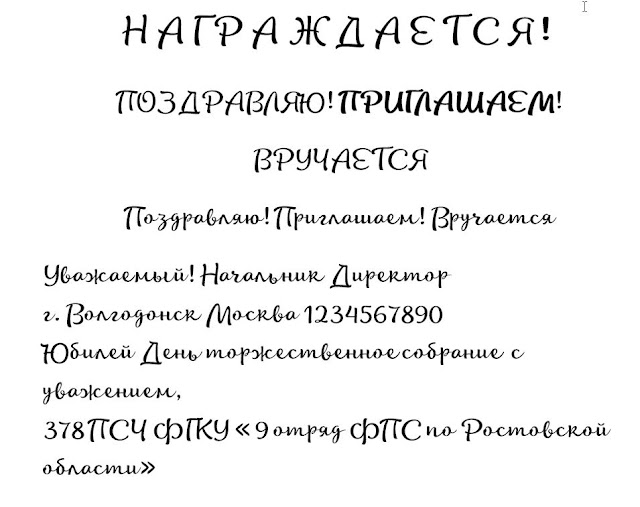
Правила выбора шрифтов. Внедрение шрифта в презентацию. презентация, доклад
Шрифты:
как выбрать шрифт?
как внедрить шрифт в презентацию?
MS Office Power Point
Как выбрать шрифт для презентации
Правило первое
ШРИФТ ДОЛЖЕН БЫТЬ ЛЕГКО ЧИТАЕМЫМ.
Потому отдавайте предпочтение шрифтам без засечек. Образцами таких шрифтов являются Arial, Calibri, Century Gothic, Verdana.
Это не значит, что нужно совсем отказаться от изысканных шрифтов с засечками. Используйте их в заголовках – крупные буквы будут читаться легче.
Как выбрать шрифт для презентации
Правило второе
ИСПОЛЬЗУЙТЕ ДОСТАТОЧНЫЙ РАЗМЕР ШРИФТА.
Помните, что шрифт с кеглем менее 18 вообще неприемлем для публичных выступлений.
Шрифт размером до 24 подходит для идеальных условий – когда проектор яркий, освещение соответствующее, и аудитория сидит недалеко. Так что лучше всего использовать размер шрифта не менее 24.
Как выбрать шрифт для презентации
Правило третье
НЕ ПЕРЕБОРЩИТЕ С КОЛИЧЕСТВОМ.
Слайды, на которых слишком большой разброс в размерах шрифтов или слайды, где использовано слишком много разных шрифтов, выглядят нагромождёнными и тяжелы для восприятия.
Удобно использовать один шрифт для заголовков и один для основного текста.
Как выбрать шрифт для презентации
Правило четвёртое
РАССТАВЛЯЙТЕ АКЦЕНТЫ ПРАВИЛЬНО.
Как выбрать шрифт для презентации
Правило пятое
ПОМНИТЕ О СОЧЕТАЕМОСТИ
Шрифты, которые Вы используете, должны соответствовать общему дизайну презентации и не конфликтовать между собой.
Это довольно трудный навык, для таких непрофессионалов, как мы, дизайнеры даже составляют специальные таблицы сочетаемости. Экспериментируйте!
Как выбрать шрифт для презентации
Правило шестое
БУДЬТЕ ВНИМАТЕЛЬНЫ С НЕСТАНДАРТНЫМИ ШРИФТАМИ.
Для заголовков в презентации о космосе подойдёт вот такой шрифт, а учителя русского языка уважают за элегантность шрифт Прописи. Как сделать так, чтобы нестандартный шрифт, имеющийся на Вашем домашнем компьютере, корректно отображался в классе или у коллеги?
Внедрение шрифта в презентацию (MS Office Power Point 2007)
Шаг первый
Откройте презентацию Power Point.
Шаг второй
Нажмите кнопку Microsoft Office
(в левом верхнем углу экрана).
Внедрение шрифта в презентацию
Шаг третий
В открывшемся меню
выбираем
«Параметры
Power Point»
Внедрение шрифта в презентацию
Шаг четвёртый
В новом окне
выбираем
вкладку
«Сохранение»
Внедрение шрифта в презентацию
Шаг пятый
Ставим галочку
«Внедрить
шрифты в файл».
Для сохранения
нажимаем «ОК»
Внедрение шрифта в презентацию
Вуаля!
Пять простых шагов и можно не переживать за то, как будет выглядеть ваша презентация на чужом компьютере.
Обратите внимание, что в других версиях Office (1997-2003, 2010) алгоритм может незначительно отличаться от приведённого, но внедрение шрифтов всегда можно найти на вкладке «Сохранение».
Метод встраивания шрифтов в PowerPoint для Mac
Когда вы отправляете по электронной почте презентацию PowerPoint, а у получателя не установлен шрифт, Microsoft Office показывает шрифт по умолчанию.
Это может изменить макет документа и придать ему другой вид. Встраивание шрифтов — это способ решения проблемы, который приводит к тому, что вся информация о шрифте выглядит так, как она выглядит в PDF-файле. Независимо от того, какие шрифты есть у других, они увидят документ с теми шрифтами, которые использовали вы. Но как вставить шрифты в PowerPoint для Mac? В этой статье вы найдете руководство по встраиванию шрифтов в PowerPoint.
Как встроить шрифты в PowerPoint для Mac
PowerPoint — это одно из приложений Office, позволяющее встраивать шрифты. Однако так было не всегда. Например, Office для Mac 2011 не поддерживает встроенные шрифты. Microsoft Office изменил это в пакете Office 2016, поэтому PowerPoint 2016 может корректно отображать шрифты, встроенные в файл. Учитывая это, давайте рассмотрим, как встроить шрифты в PowerPoint для Mac. Это руководство предназначено для PowerPoint для Office 365 для Mac и PowerPoint 2019 для Mac. Эти версии поддерживают встроенные шрифты, в то время как Word 2019 и Excel 2019 для Mac не поддерживают встроенные шрифты.
- Шаг 1. Откройте файл PowerPoint, в который вы хотите встроить шрифты, а затем перейдите в меню и выберите «Параметры»..
- Шаг 2. Откроется диалоговое окно, в котором выберите пункт «Вывод и общий доступ» и нажмите кнопку «Сохранить».
- Шаг 3. В разделе «Встраивание шрифтов» выберите опцию «Встраивать шрифты в файл».
Теперь при сохранении файла используемые шрифты будут встроены в презентацию. Следует помнить несколько моментов. Во-первых, нужно избегать использования опции «Встроить только символы, используемые в презентации». Гораздо лучше внедрить все символы шрифта. Таким образом, получатель сможет редактировать файл при необходимости.
Совместное использование двух шрифтов добавит разнообразия и целеустремленного стиля вашей презентации, а сильные стороны каждого шрифта будут работать на вашу презентацию, а не против нее.
Обратите внимание, что шрифты без засечек почти всегда несут в себе более современный вид, в то время как шрифты с засечками часто, но не всегда, немного более серьезные, а иногда даже скучные.